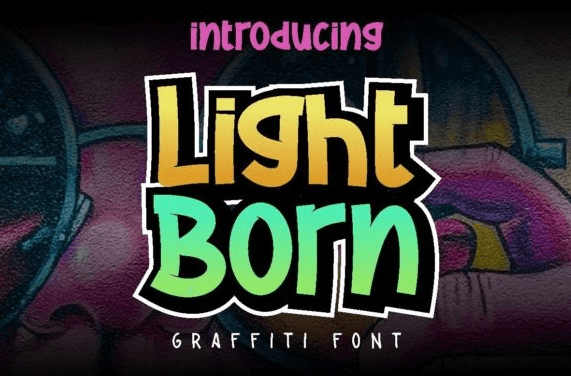
Light Born Font
Light Born - это веселый и красочный шрифт.
Он отличается урбанистическим стилем, который усилит каждый дизайн, который вы хотите развить.